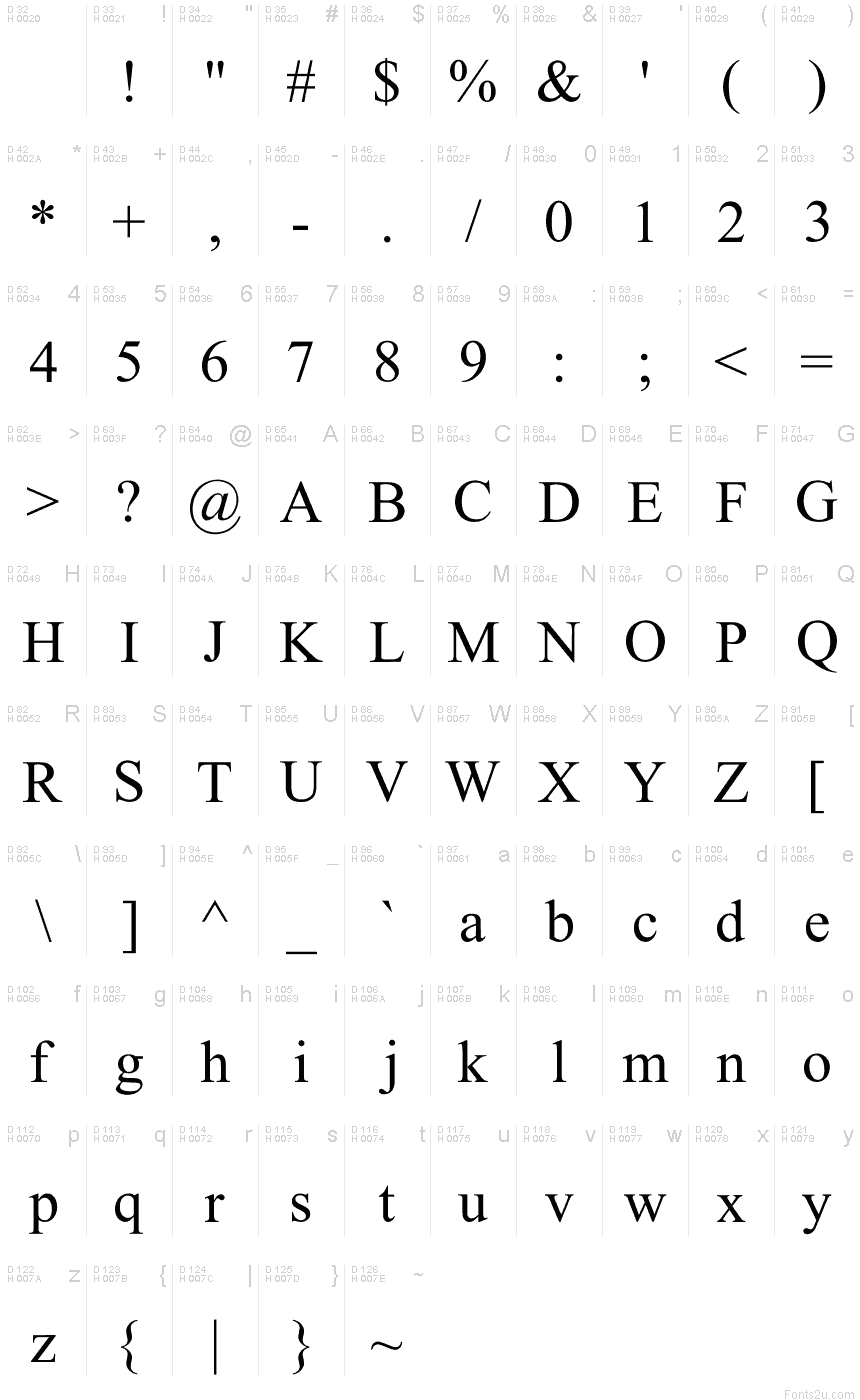
Temps Nouveau من Digital Graphic Labs هو خط مجاني عالي التباين يتميز بلمسة تحريرية راقية من أواخر القرن التاسع عشر. تمزج الحروف بين الخطوط الطويلة والرفيعة مع زوائد واضحة ومنحنيات ناعمة، مما يضفي طابعاً رسمياً دون أي جمود.
يتناسب الخط بشكل طبيعي مع عناوين المجلات وأغلفة الكتب وتصميمات الموضة والملصقات والهوية البصرية التي تتطلب لمسة درامية. وباعتباره خطاً مجانياً، فهو مثالي للاستخدام في العناوين القصيرة والرسوم الأحادية (المونوغرام) وبطاقات العناوين، حيث تمنح الخطوط الرأسية الطويلة والزوائد الحادة الحروف حضوراً أدبياً متوازناً.